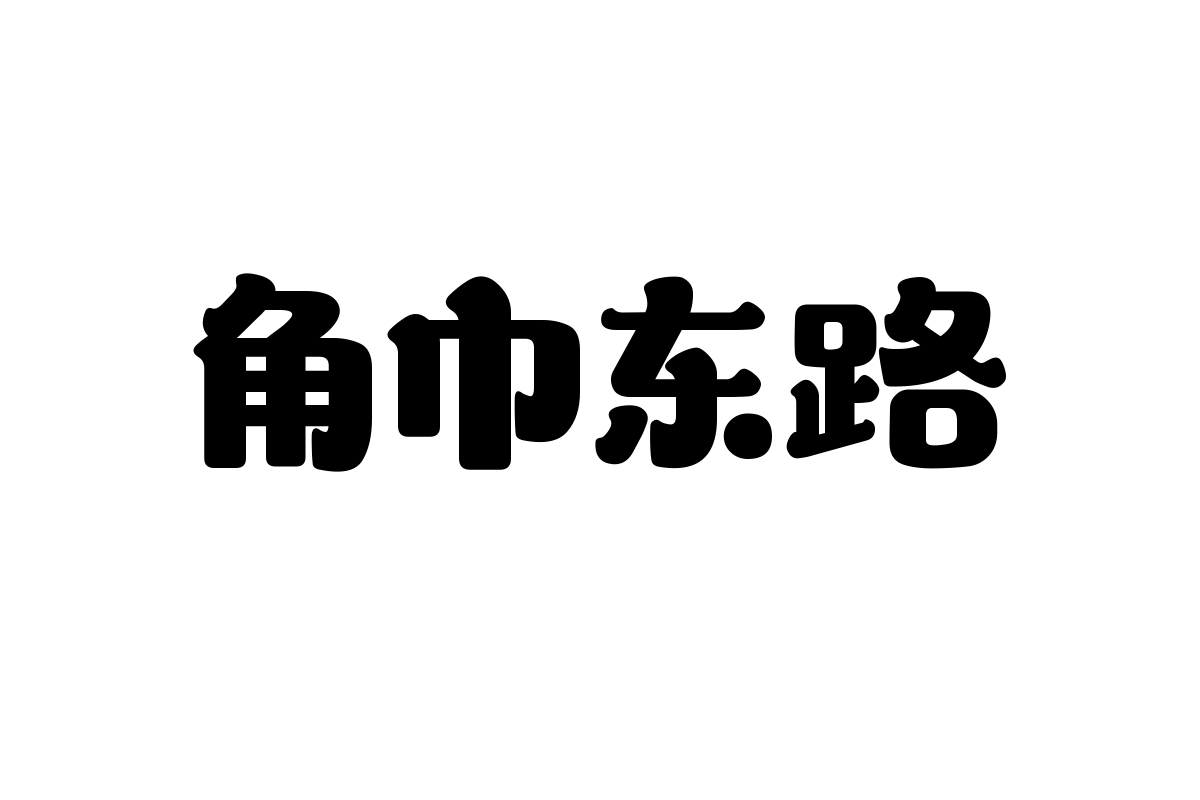
山海小龙猫字体是一款具有独特设计元素的中文字体,由国内设计师团队打造。这款字体结合了现代与古典元素,通过创新的笔画和结构,呈现出一种既优雅又活泼的风格。
山海小龙猫字体的特点如下:
1. 字形设计:这款字体采用了独特的字形设计,使得每个字符都显得生动有趣。例如,“山”字采用了山峰的形状,而“海”字则融入了海浪的元素,形成了独特的视觉效果。
2. 笔画流畅:山海小龙猫字体的笔画流畅自然,没有过多的装饰,给人一种简约而不失美感的感觉。这种简洁的线条处理,使得字体在视觉上更加突出。
3. 风格多样:这款字体适用于各种场合,无论是用于书籍、杂志、海报还是网页设计,都能展现出其独特的魅力。同时,它也可以与其他字体搭配使用,创造出丰富的视觉效果。
4. 可读性强:虽然山海小龙猫字体的设计感十足,但其可读性依然出色。每个字符的大小、间距和位置都经过精心设计,使得阅读体验更加舒适。
总之,山海小龙猫字体是一款集美观、实用于一体的中文字体,适合用于需要强调个性和创意的设计项目中。